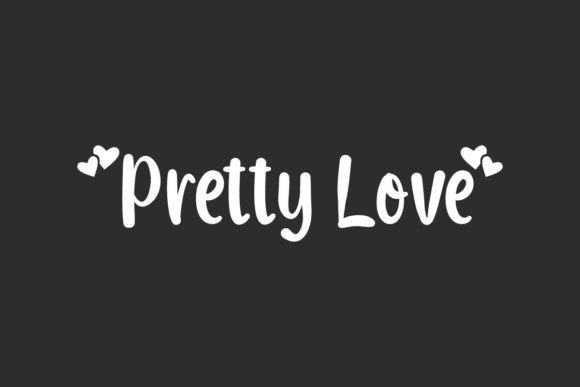
Pretty Love
Se stai cercando risorse di alta qualità come Pretty Love, questo pacchetto premium è una scelta fantastica per i tuoi progetti creativi.
Realizzato con precisione, Pretty Love fornisce vettori puliti, tipografia fluida e una licenza commerciale per la massima tranquillità.
Che tu stia creando prodotti POD (Print on Demand), partecipazioni di nozze o grafiche per i social media, Pretty Love è la scelta ideale.